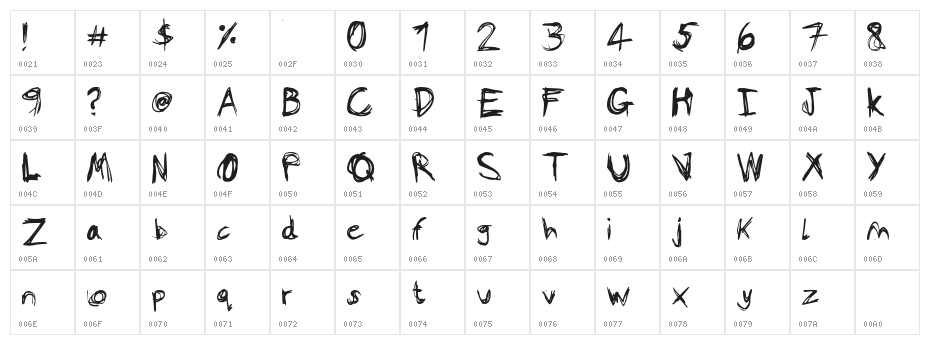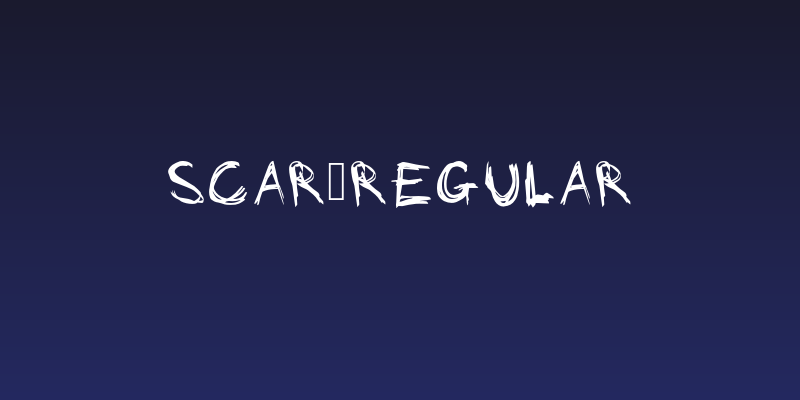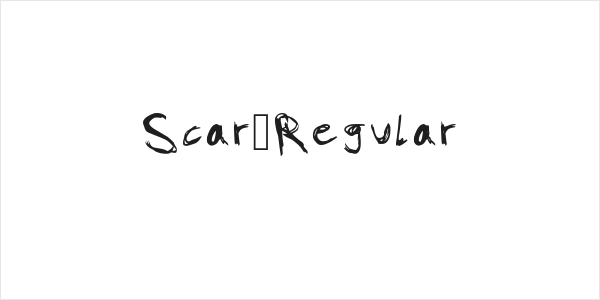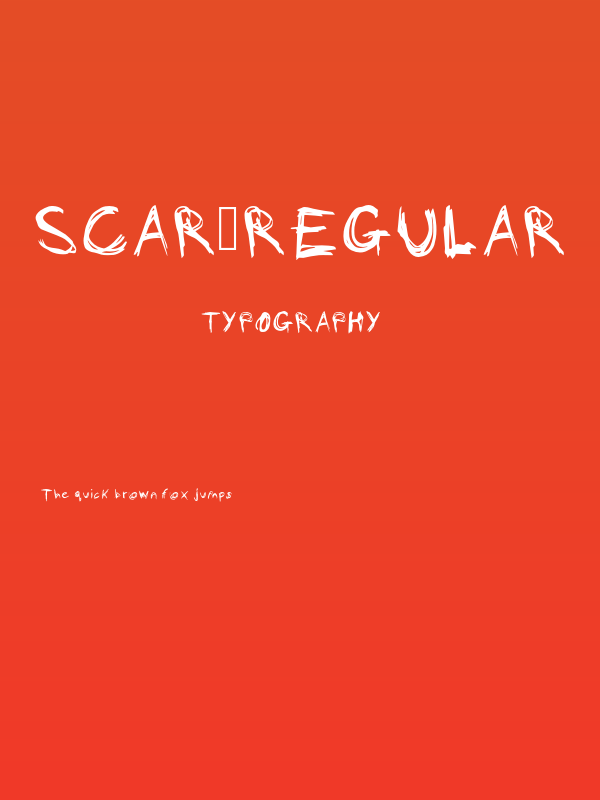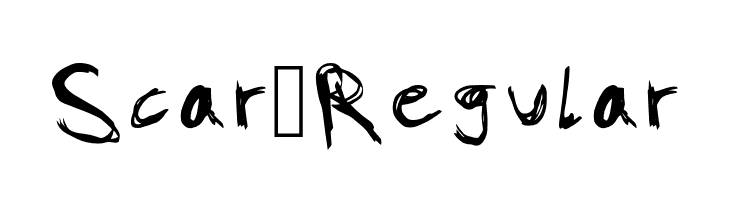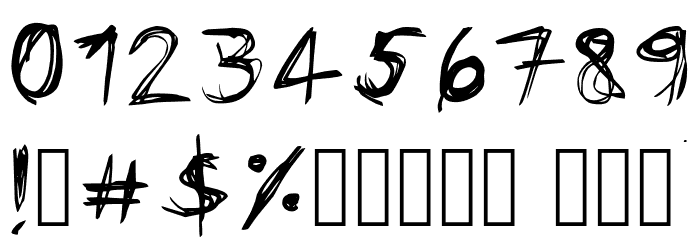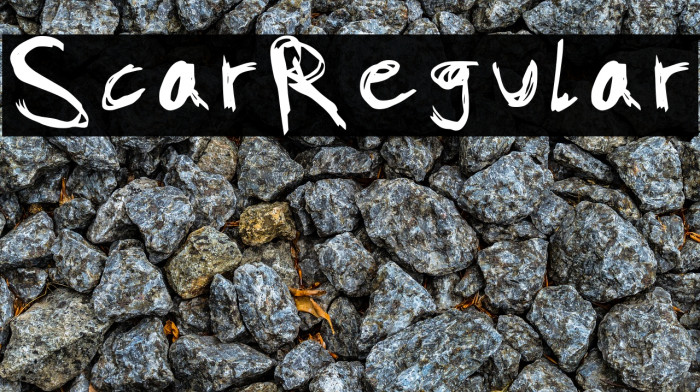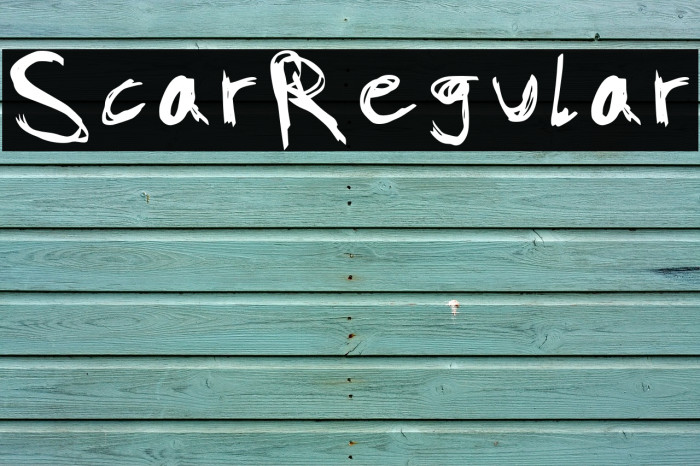
Scar-Regular Font
| Caz de utilizare | Headlines, Posters, Album covers |
| Proiecte propuse | Ideal for horror-themed designs, edgy posters, album covers, or any project requiring a bold, artistic statement. |